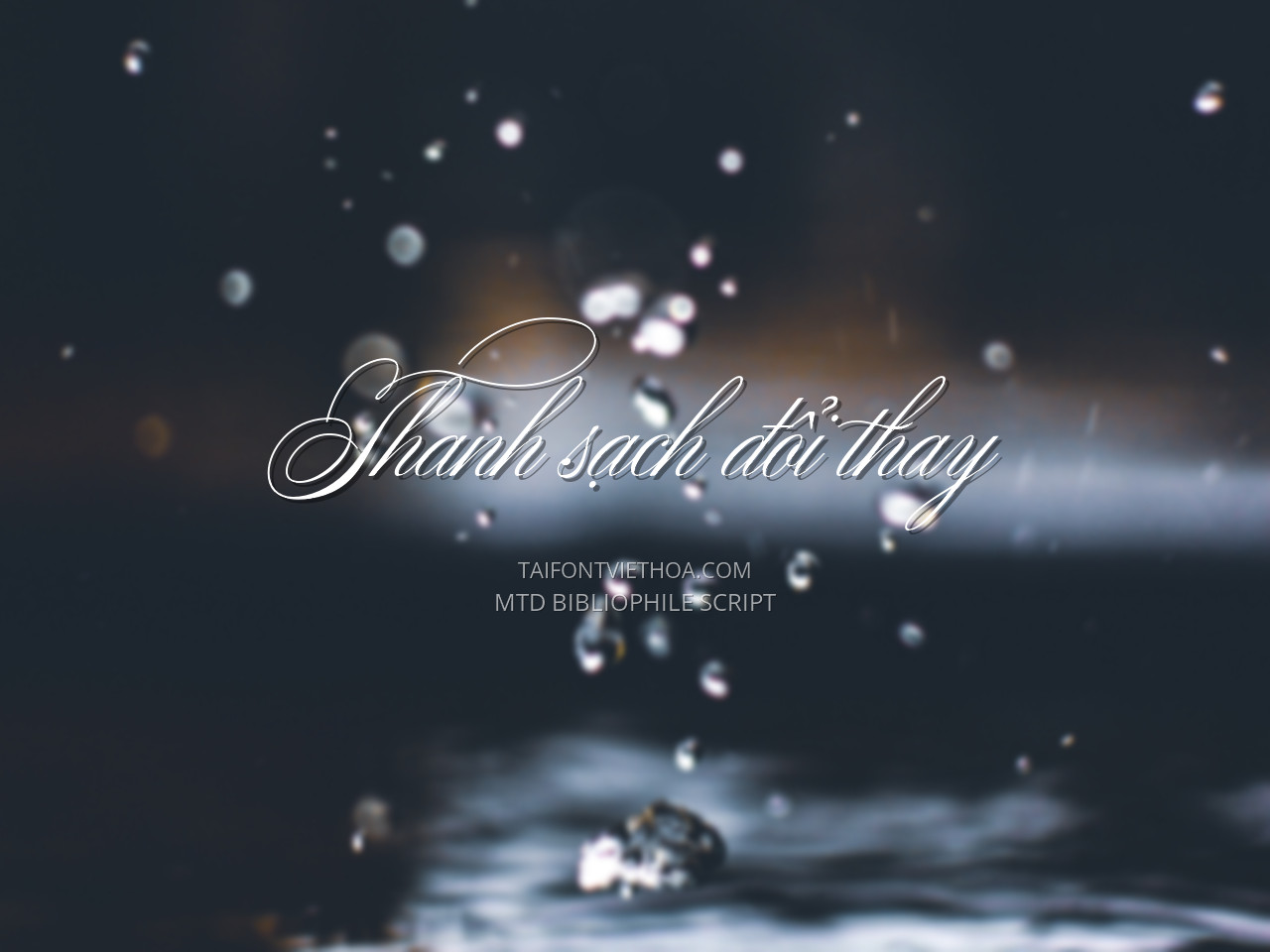
Giới thiệu về font Bibliophile Script – Vẻ đẹp thư pháp lãng mạn dành cho người yêu chữ
Bibliophile Script là một kiểu chữ viết tay mang phong cách thư pháp hiện đại, được thiết kế dành riêng cho những ai yêu thích sự thanh lịch, nghệ thuật và đậm chất cá nhân. Tên gọi “Bibliophile” có nghĩa là “người yêu sách” – và quả thật, font này mang đến cảm giác như từng con chữ được viết nắn nót bằng mực, thể hiện sự trân trọng ngôn từ trong từng nét bút. Font thường được ứng dụng trong các thiết kế cần yếu tố tình cảm, nhẹ nhàng hoặc cao cấp như: thiệp cưới, thương hiệu handmade, trích dẫn truyền cảm hứng,…
Đặc điểm nghệ thuật và ứng dụng phù hợp của Bibliophile Script
Font Bibliophile Script sở hữu các nét bút cong nhẹ, kết nối mạch lạc giữa các ký tự, cùng độ nghiêng mềm mại mô phỏng nét viết tay bằng bút mực cổ điển. Font đi kèm với nhiều swash (đuôi chữ cách điệu), ligatures và glyph thay thế, giúp người dùng dễ dàng tạo nên layout chữ giàu biểu cảm và tính cá nhân cao. Đây là font lý tưởng cho các thiết kế cần truyền tải cảm xúc một cách tinh tế.
Font đặc biệt phù hợp với các thiết kế như: thiệp cưới nghệ thuật, giấy mời sự kiện cao cấp, bộ nhận diện thương hiệu cá nhân, logo mỹ phẩm thủ công, bìa sách thơ, thư pháp số, hoặc bài viết truyền cảm hứng. Ngành nghề phù hợp gồm: ảnh cưới – thiệp cưới, sự kiện, spa – làm đẹp, thương hiệu handmade, sản phẩm thủ công, thời trang nữ hoặc các dự án mang hơi thở lãng mạn và nghệ thuật cá nhân.